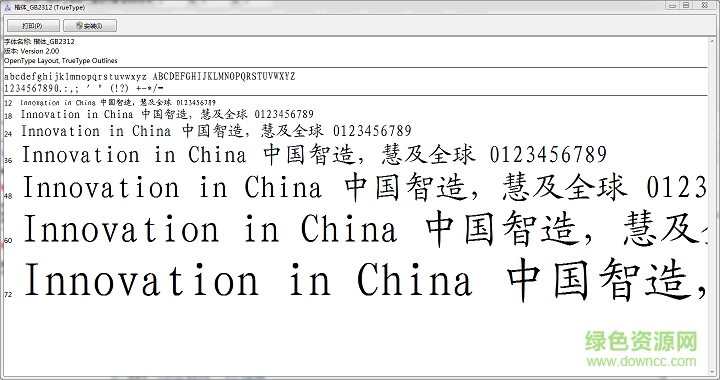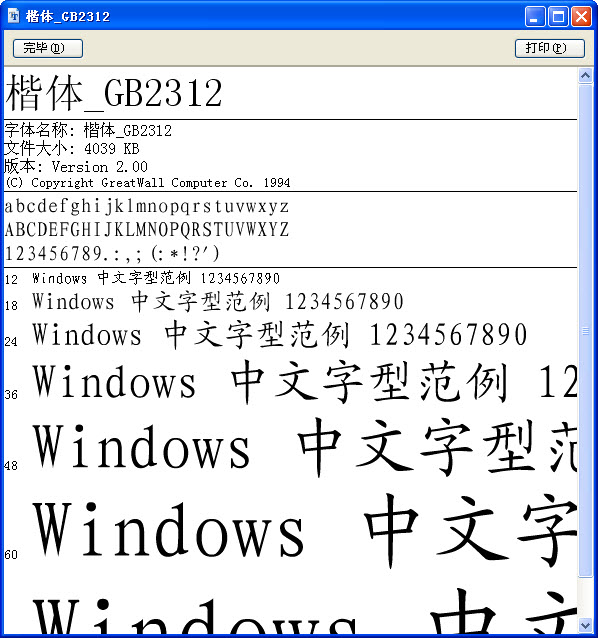
兩者之間的相同點:都是微軟office的字體,可以在打印時使用。
兩者之間的不同點: 楷體”這種字體字形沒有楷體GB2312那么舒展(它是GB2312內(nèi)碼,收字6763個),有點像漢儀公司的楷體;從外觀看,兩種種字體有些相似,但在具體的字高字寬比例、字大小、字默認(rèn)行間距等方面是有細(xì)微的差別的??w-GB2312(執(zhí)行GB2312-1980標(biāo)準(zhǔn),因而得名),它收字也是6763個。GB2312是國標(biāo)的體。就像仿宋和仿宋GB23130,是 GB2310就是國標(biāo)體。
一般打印都用的是國標(biāo)體,通常公文的二級標(biāo)題會采用楷體-GB2312。